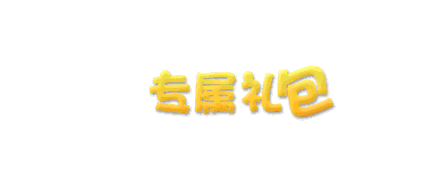
Q版字体第二波
原来发过一个Q版字体小心的,在来一次
先来一个完成的
GIF动态分解图
第一步选择一个字体,最好笔画粗壮一些。。(为何又是这货)
添加图层样式,下面献上参数。
这个颜色可根据背景图片,个人喜欢变换。
这步比较重要,复制一层进行描边处理,用于给文字上背景层,然后变成智能对象,方便以后操作。
这个就需要上一步转换为智能对象了,不然描不了边。
最后进行细节处理,调整。